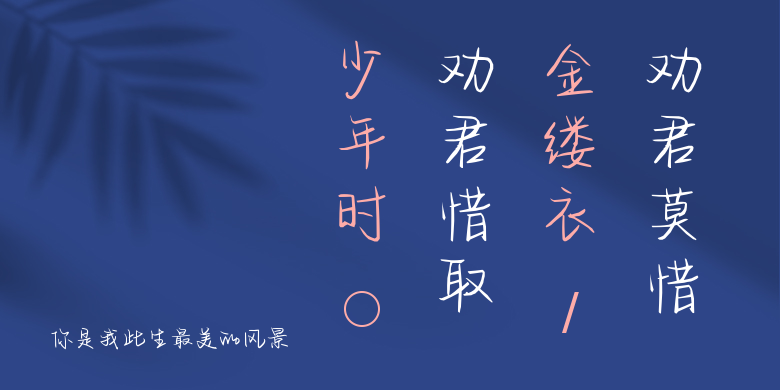
你是我此生最美的风景
你是我此生最美的风景,这款字体结构工整、笔画清晰,兼顾美观与易读性,适用于标题、正文、海报、包装、LOGO 等多种场景。字形优雅稳定,风格百搭耐看,适配日常排版与创意设计,让文字呈现更舒适、更具质感。你是我此生最美的风景一笔一画,皆是细节,以均衡的比例、流畅的线条打造舒适视觉体验,字形端正大气,风格简约现代。无论是商业设计、品牌宣传还是日常排版,都能轻松驾驭,让文字更有格调与力量。你是我此生最美的风景字体下载。